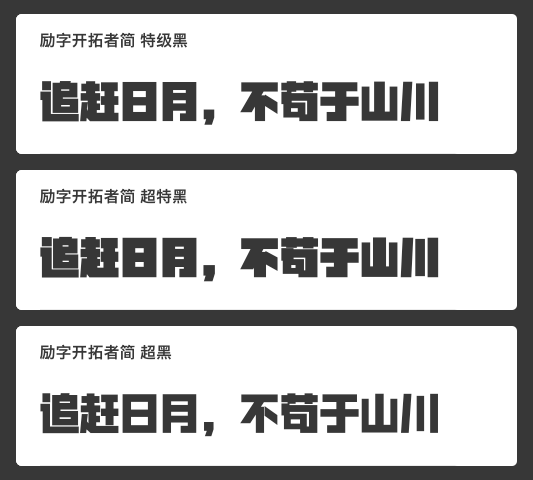
三款创意黑体字推荐,为你的设计注入力量与个性
在设计中,字体的选择往往决定了作品的风格和气质。对于追求力量感、个性化和视觉冲击力的设计师来说,黑体字是一个经典且实用的选择。今天,为大家推荐三款极具创意的黑体字体,它们各具特色,能够满足不同设计场景的需求。
1. 励字开拓者简
励字开拓者简 是一款极具现代感的黑体字体,字型方正,中宫较大,重心适中,整体设计简约而不失力量感。其笔画全部采用直线处理,横平竖直,棱角分明,起笔和收笔以平切为主,带有强烈的镜像视觉效果。这款字体的特别之处在于对部分钩笔画进行了去钩处理,撇、捺、点则运用竖直的处理方法,整体风格统一且富有几何美感。此外,励字开拓者简 超黑还包含了许多网红流行用字,如“囍”“䨻”“燚”等,非常适合用于标题设计、品牌标识或社交媒体内容,能够为作品增添一份现代感和视觉冲击力。字体一共三款字重,无论哪款字重都能能完美适配于您的设计中。
2. 高手庆科帅黑体 大黑
高手庆科帅黑体 大黑是一款直线黑体字体,整体风格硬朗且倾斜,中宫略大,布白均匀,重心统一。其笔画设计简约,横细竖粗,起笔和收笔以平切为主,折笔处的尖锐部分经过优化处理,整体倾斜约6度,视觉上更具动感和张力。西文符号的设计也沿袭了中文的特点,以直线为主并加入倾斜处理,使中英文搭配更加协调统一。这款字体非常适合用于运动品牌、科技类设计或广告海报,能够为作品注入一份力量感和速度感。
3. 励字铁拳简 超级黑
励字铁拳简 超级黑是一款极具视觉冲击力的创意黑体字,笔画粗壮,字面宽大,整体设计饱满且富有块面感。其折角圆润的设计犹如铁拳出击,横扫千军,非常适合用于需要强烈视觉表现的设计场景。这款字体的风格大胆且富有张力,能够瞬间吸引观众的注意力,非常适合用于品牌标识、活动海报或游戏界面设计,为作品增添一份霸气和个性。
以上三款创意黑体字体各具特色,无论是现代感十足的励字开拓者简、动感硬朗的高手庆科帅黑体 大黑,还是力量感爆棚的励字铁拳简 超级黑,都能为你的设计注入独特的风格和视觉冲击力。赶快尝试这些字体,让你的作品在众多设计中脱颖而出吧!